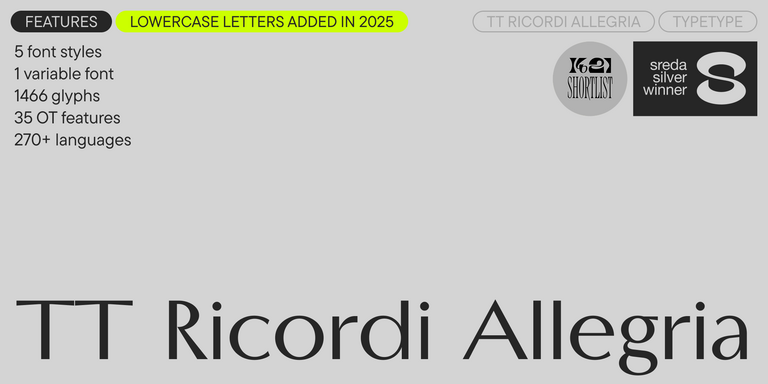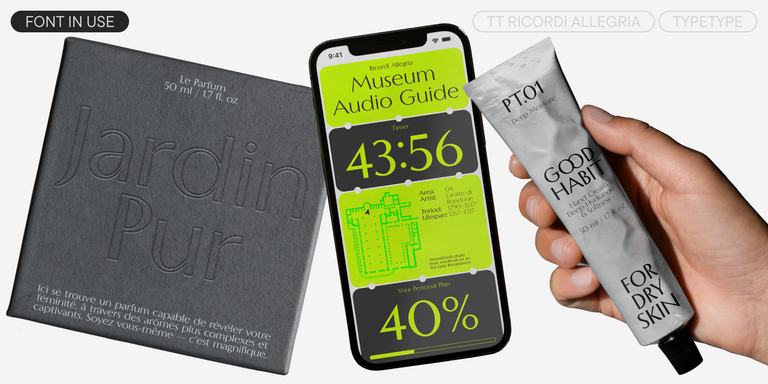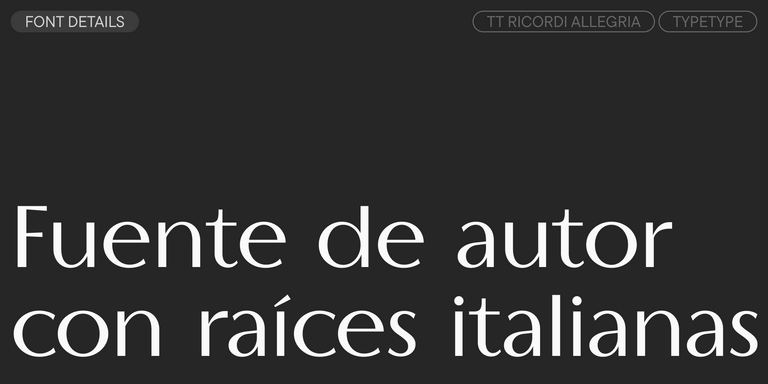
TT Livret es una serif elegante, moderna y funcional.
Fuentes similares a Rinat
Si estás cansado de las fuentes desgastadas y busca tipos de letra similares a Rinat, consulta nuestras principales alternativas a Rinat. Estas son fuentes que tienen características similares, pero al mismo tiempo tienen características de diseño nuevas y únicas. Por ejemplo, pertenecen a la misma categoría de fuentes, son adecuadas para los mismos fines y tienen características similares, pero difieren en detalles o proporciones.
Encuentra un excelente reemplazo para Rinat e intenta emular un estado de ánimo similar usándolo en sus diseños. Cada fuente presentada en esta página es un doble de la fuente Rinat, de hecho, su análogo completo.
TT Bells combina la elegante suavidad de las Antiqua con un carácter complejo y audaz reflejado en terminales rectos y serifas en forma de flecha. La tipografía está basada en la pluma de punta ancha, responsable de estos característicos terminales y serifas.
TT Ricordi Allegria es una grotesca florentina contemporánea, elegante e inteligente.
TT Ramillas es una serif contemporánea con gran versatilidad editorial. Incluye estilos decorativos e iniciales ornamentales con motivos florales.
TT Tricks es una serif moderna para texto cuyo diseño refleja el estilo de las serifas transicionales. Esta tipografía posee un carácter sereno, elegante y moderadamente estricto.
TT Geekette es una serif variable experimental con formas de carácter amigable y flexible.
TT Alientz es una tipografía variable que permite al usuario realizar un viaje visual desde una grotesca extraterrestre hasta una display serif extremadamente afilada.